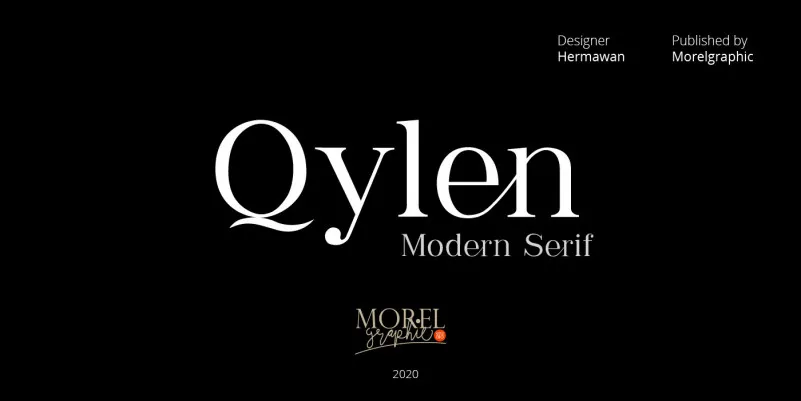
Qylen Serif Font
Aqui está uma descrição para a página de download da fonte ‘Qylen Serif Font’, mantendo os parágrafos curtos e seguindo as regras especificadas: Hamilton, designer brasileiro, criou a Qylen Serif Font com um design elegante e moderno. Esta fonte utiliza ligaturas para conectar letras em uma transição suave e fluida. Ideal tanto para aplicações gráficas como logomarcas, monogramas de casamentos ou headlines de destaque, esta fonte é perfeita para projetos de marca, identidades digitais, cartazes, flyers e até mesmo design web e convites de casamento. Com sua versatilidade, a Qylen Serif Font pode ser usada tanto em designs modernos e minimalistas quanto para um toque retro. Seja você designer gráfico ou editora, a Qylen Serif é uma escolha inteligente que adicionará estilo e personalidade aos seus projetos visuais.